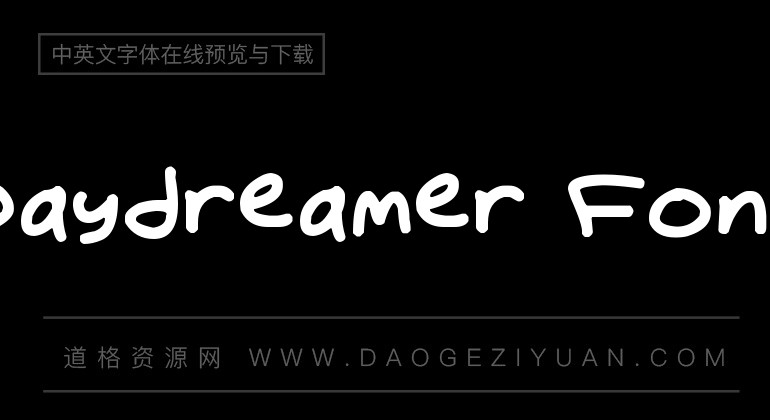
Daydreamer Font是一款免费的手写风格字体,具有轻盈、柔和的特点。它的字形流畅自然,包含了大小写字母、数字、标点符号等基本字符。除此之外,它还包含了许多特殊符号和连字符,可以在不同的排版场景中使用。Daydreamer Font适用于卡片、海报、标语、博客、书籍等多种场合,可以为你的设计带来一份温暖和感性的氛围。内容介绍
Daydreamer Font是一款非常不错的手写艺术字体,具有很好的视觉感,适合于文化类的宣传设计、商业类品牌的广告和产品包装设计以及个性化文字排版等较多场景。